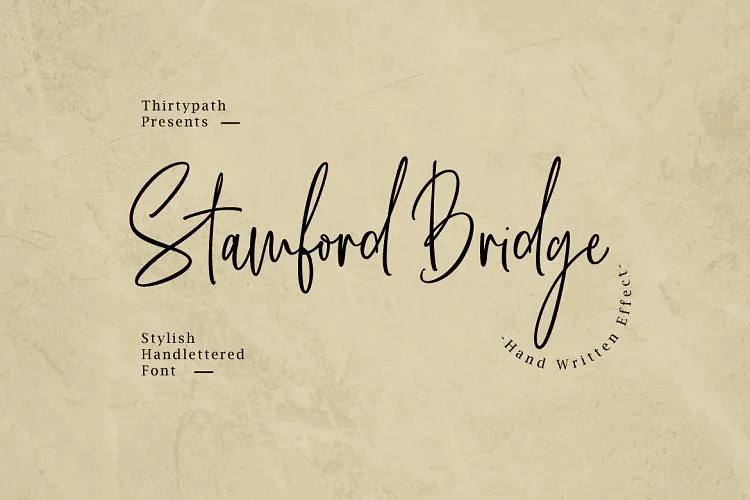
Stamford Bridge Script Font – Download Grátis
A Stamford Bridge Script é uma nova e fresca tipografia script que combina características de escrita a mão com um estilo elegante e natural. Suas linhas sutis sugerem um toque delicado de arte manual, mas não perde o equilíbrio necessário para projetos modernos e profissionais. Esse tipo é uma criação da M.0Type, designer dedicado ao mundo das fontes. Para designers, criativos e empresas, Stamford Bridge Script oferece um jeito sofisticado de inserir a essência do design manual em seus trabalhos. Perfeito para aplicar em logotipos, designs de móveis de casa ou embalagens de produtos, essa fonte é também uma elegante base para texturas que se fundem perfeitamente com imagens de fundo. Com seu estilo de escrita cuidadosamente irregular e ainda assim refinado, Stamford Bridge Script oferece um toque único à qualquer projeto em que seja usada. É perfeito tanto para a criação de logotipos como para o design das embalagens ou decorações de móveis de casa. Este é também uma ótima fonte para adicionar um toque sofisticado a qualquer imagem com fundo, tornando-a ainda mais atraente e inovadora. O que você está esperando para trazer um novo nível de elegância ao seu design?